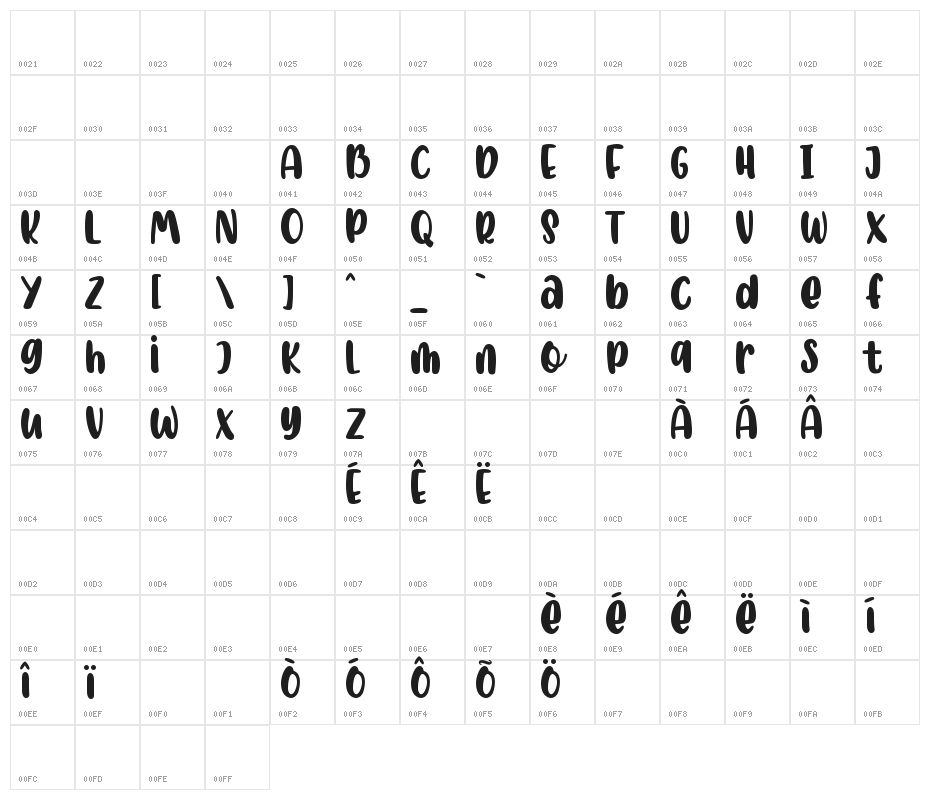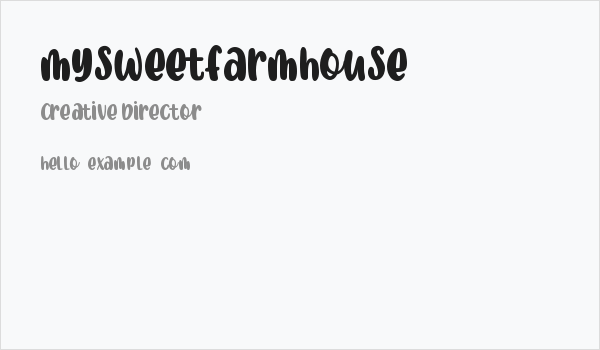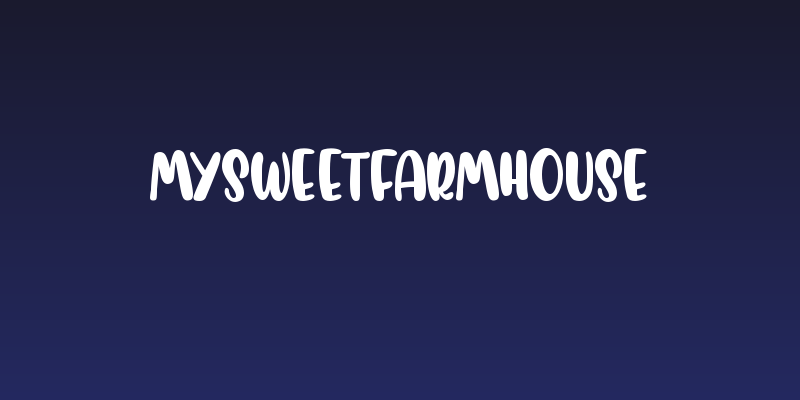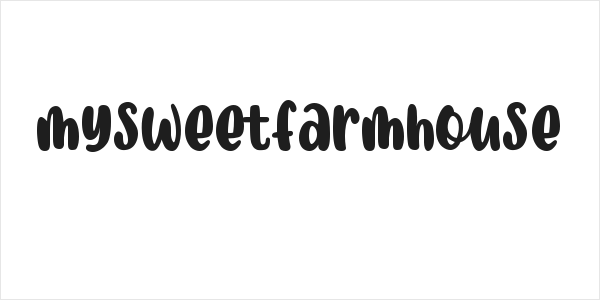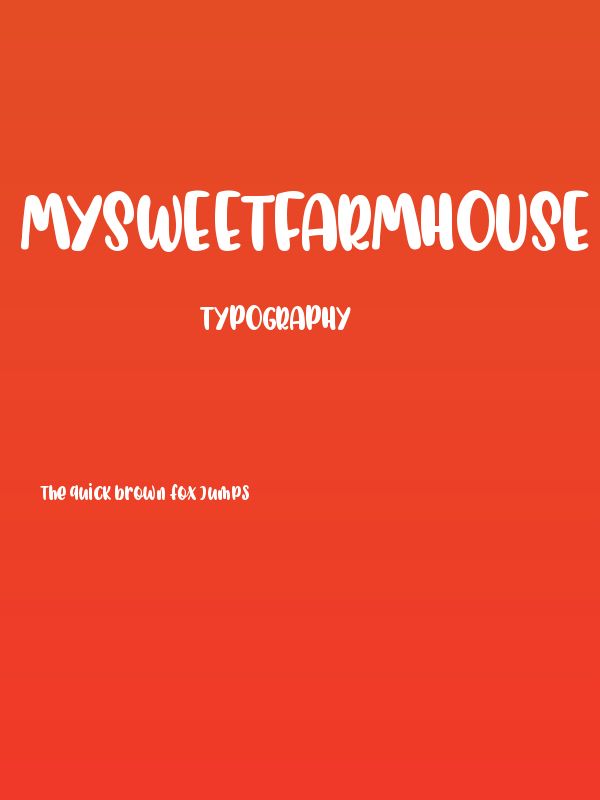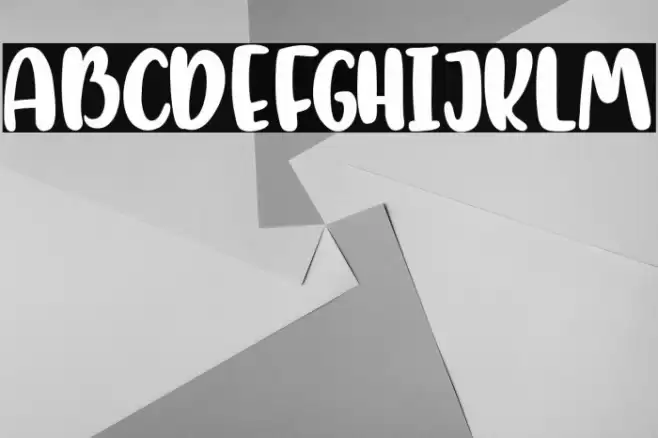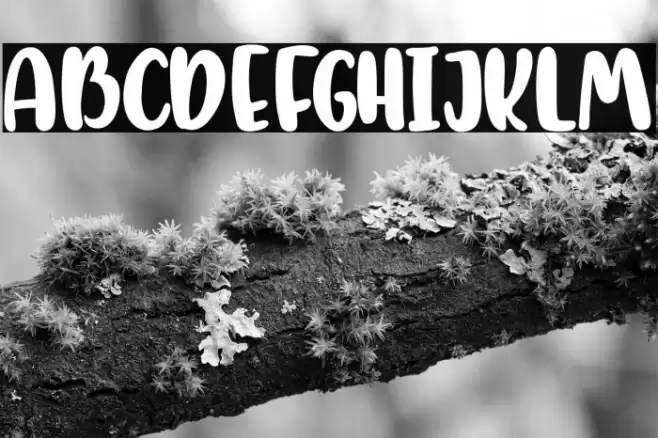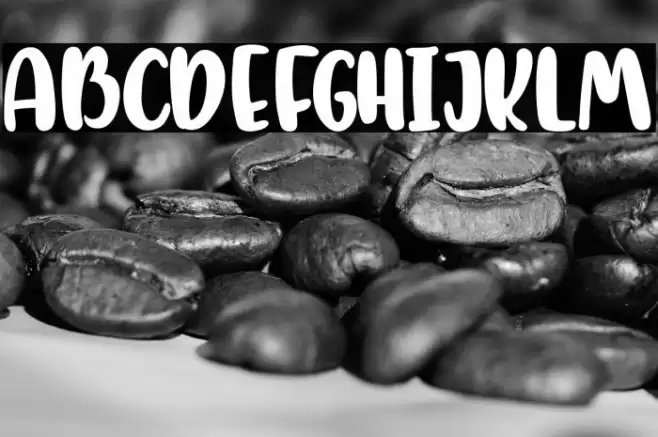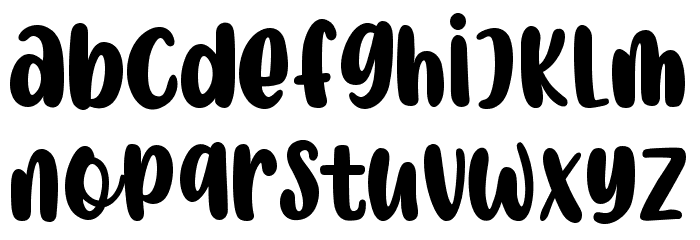
mysweetfarmhouse Font
✎ Cartoon
| Catégories | Cartoon |
| Style général | Playful |
| Projets proposés | Ideal for greeting cards, children's books, playful branding, and social media graphics. |